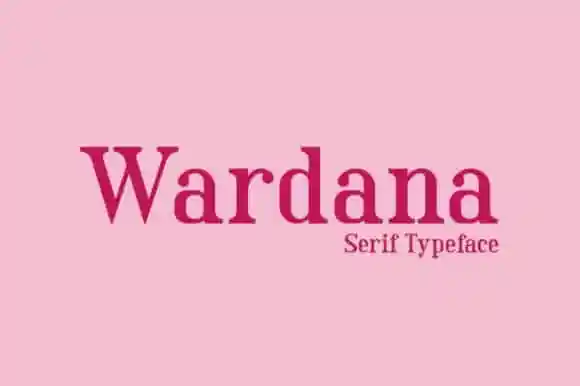
A Wardana Serif Font é uma nova família de serif moderna com grande versatilidade criativa. Com sua aguda atração, ela foi projetada pelo designer de fontes chamado AmruID. Esta tipografia serif é refinada e meticulosamente desenvolvida para se tornar um verdadeiro favorito. Convido você a experimentar o potencial desta fonte para transformar cada uma das suas ideias criativas no nível mais alto. Não perca esta oportunidade de dar um toque sofisticado e moderno ao seu próximo projeto gráfico com a Wardana Serif Font.